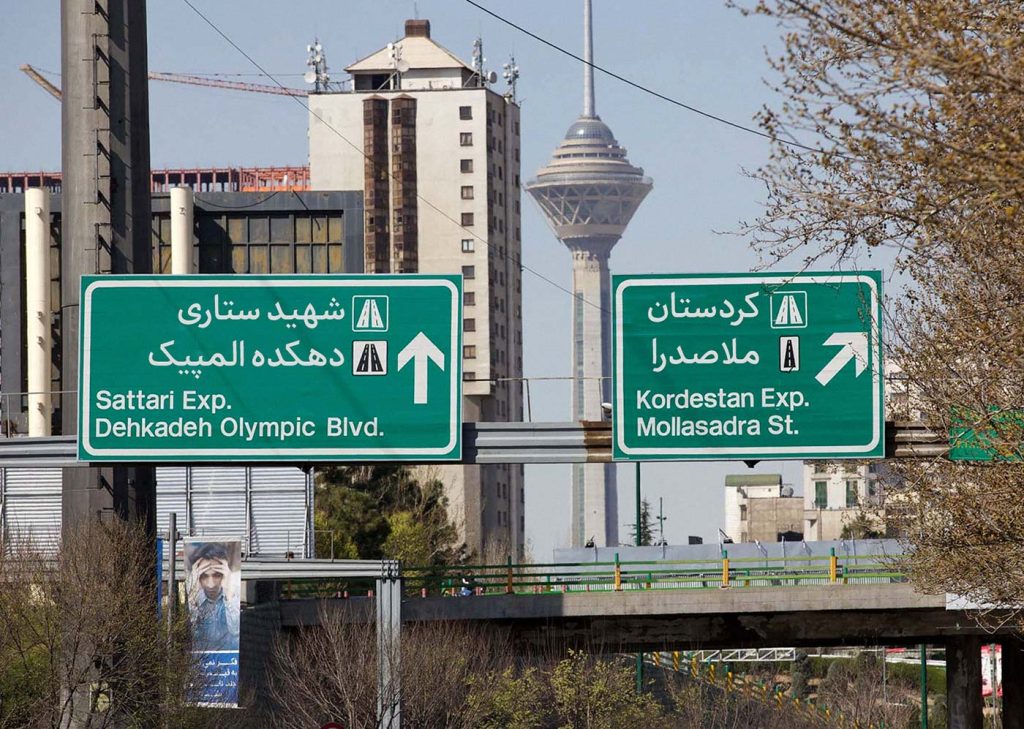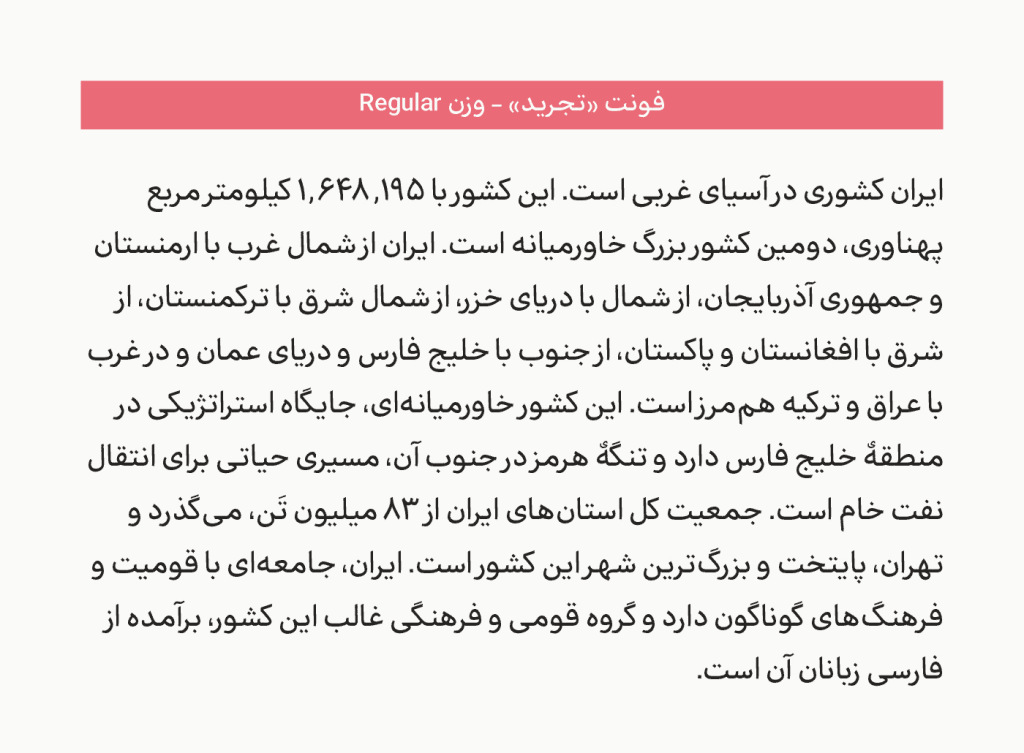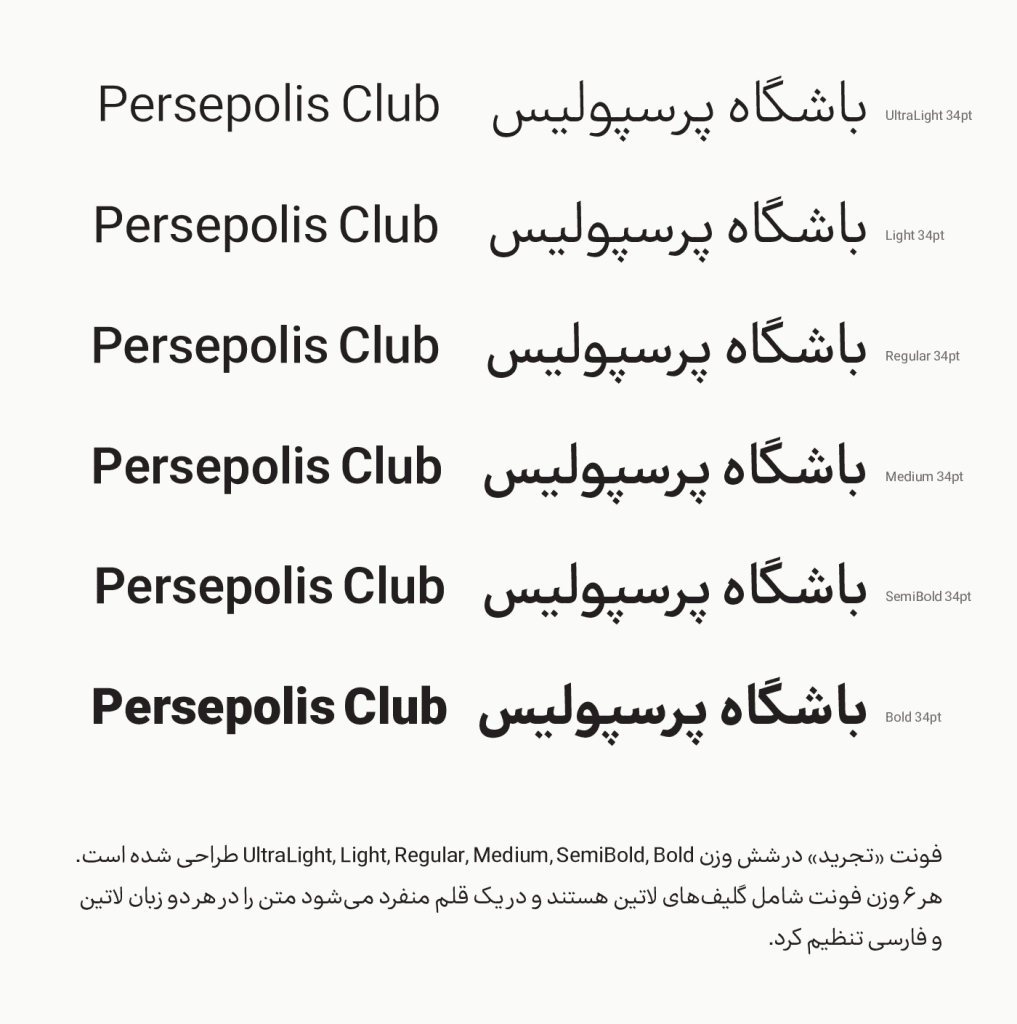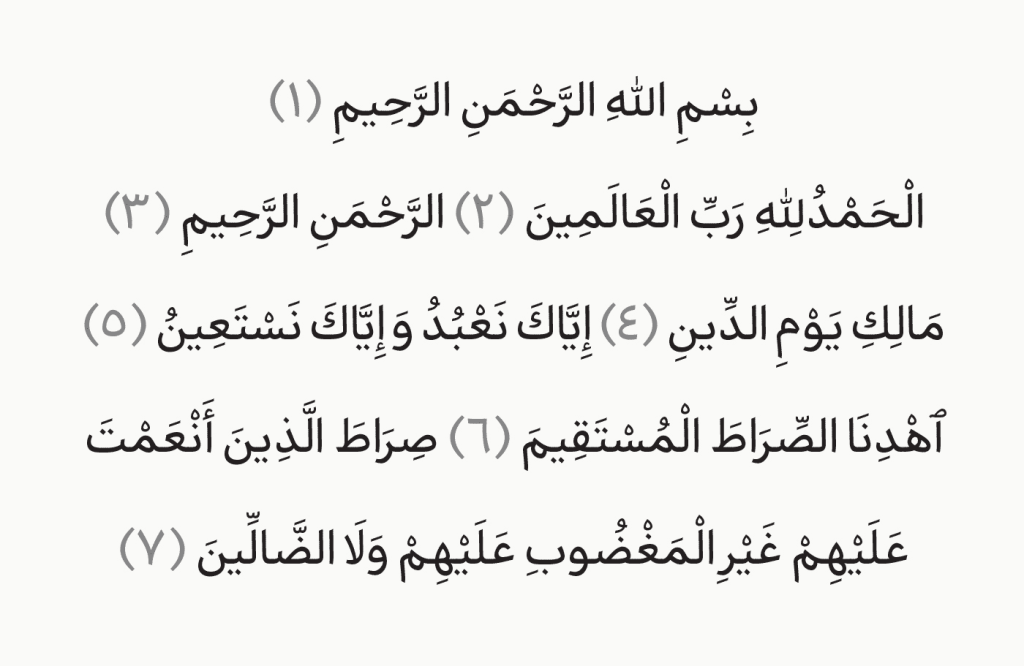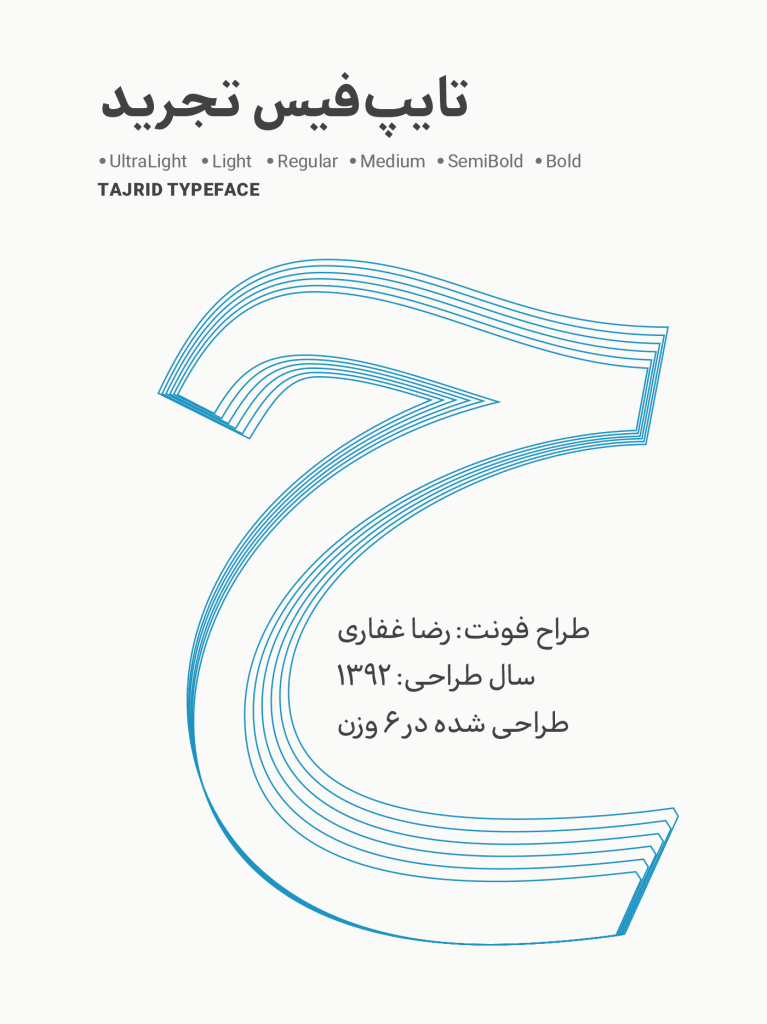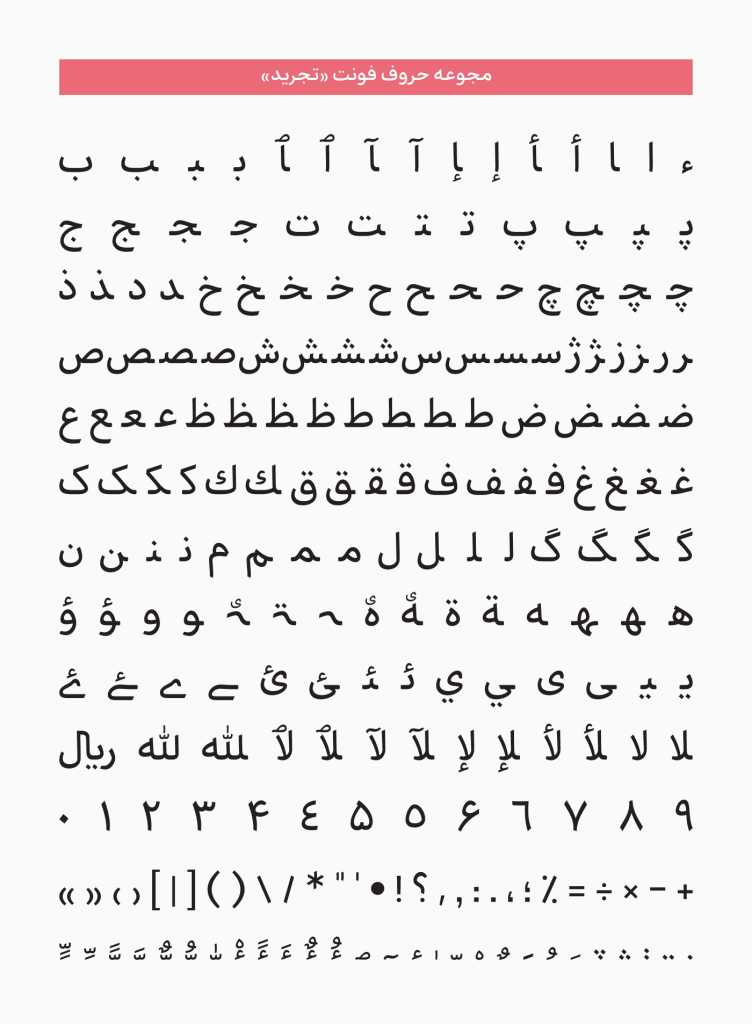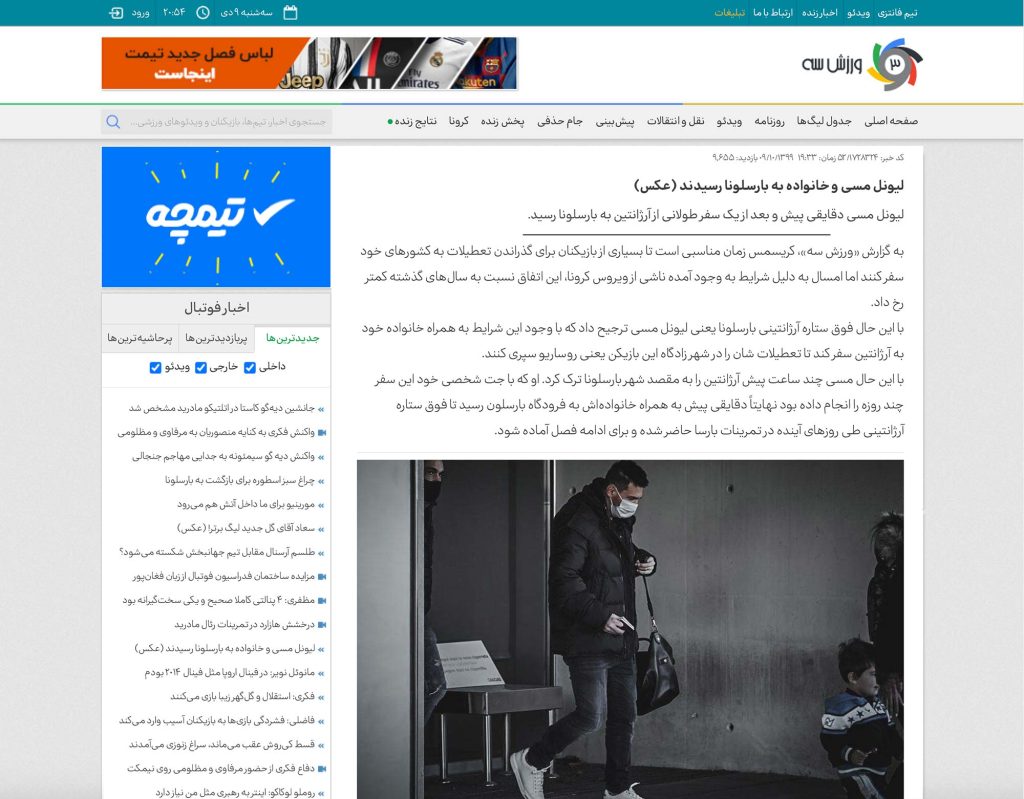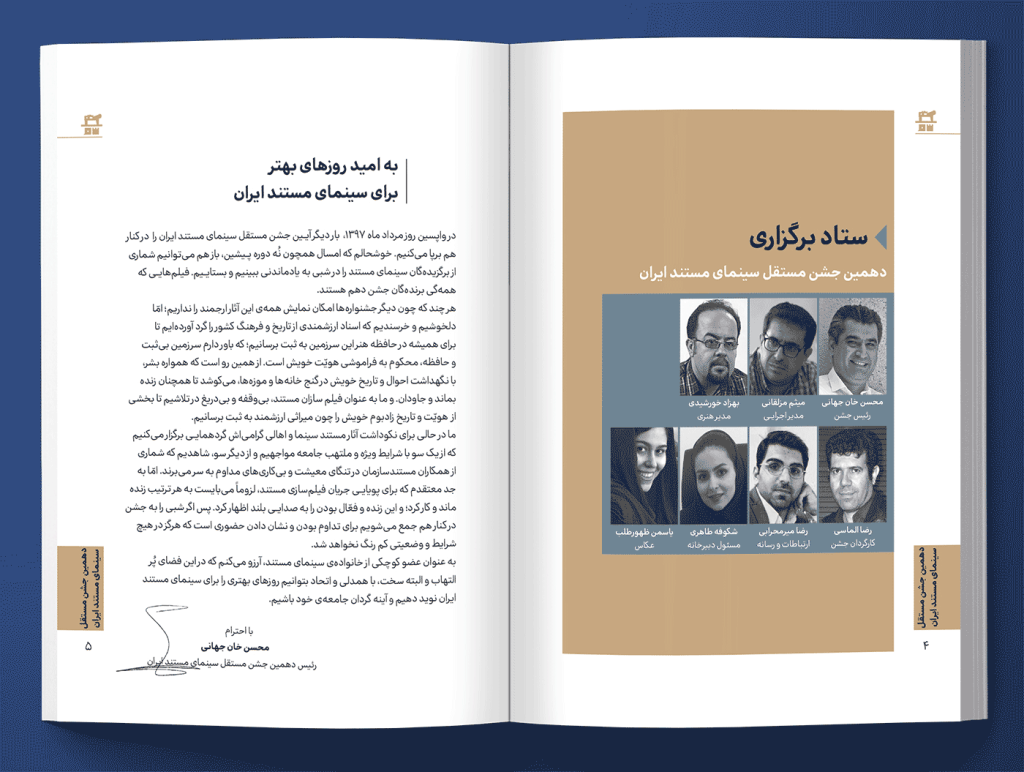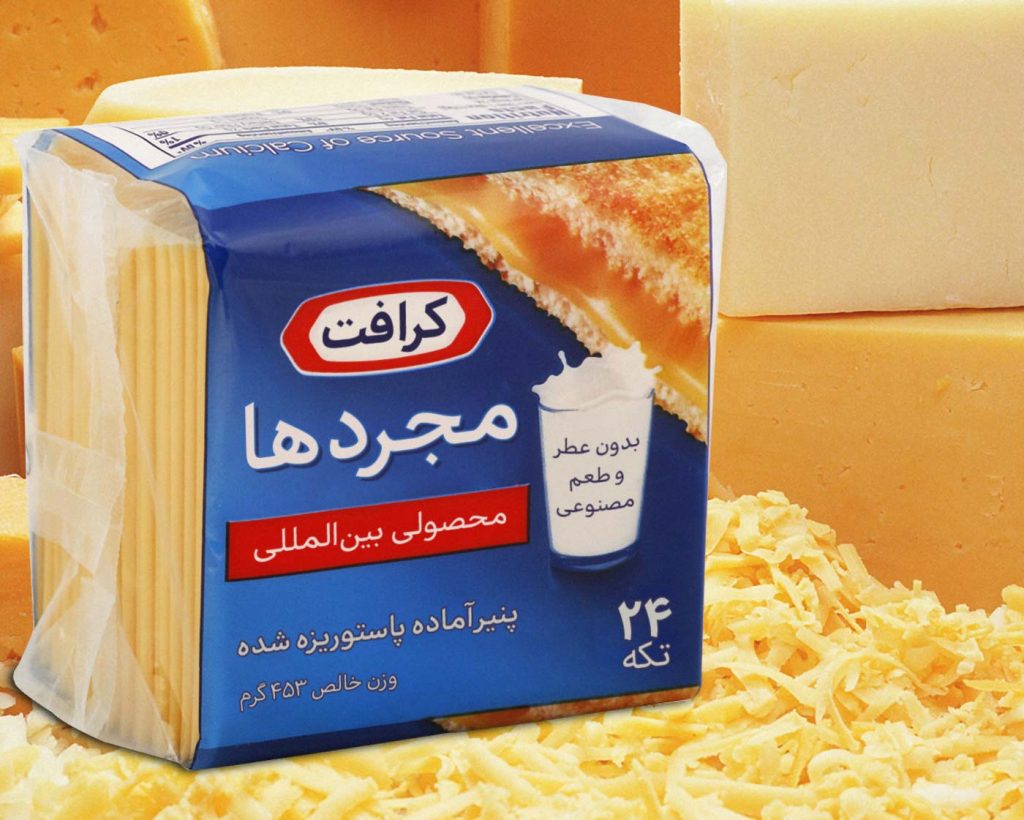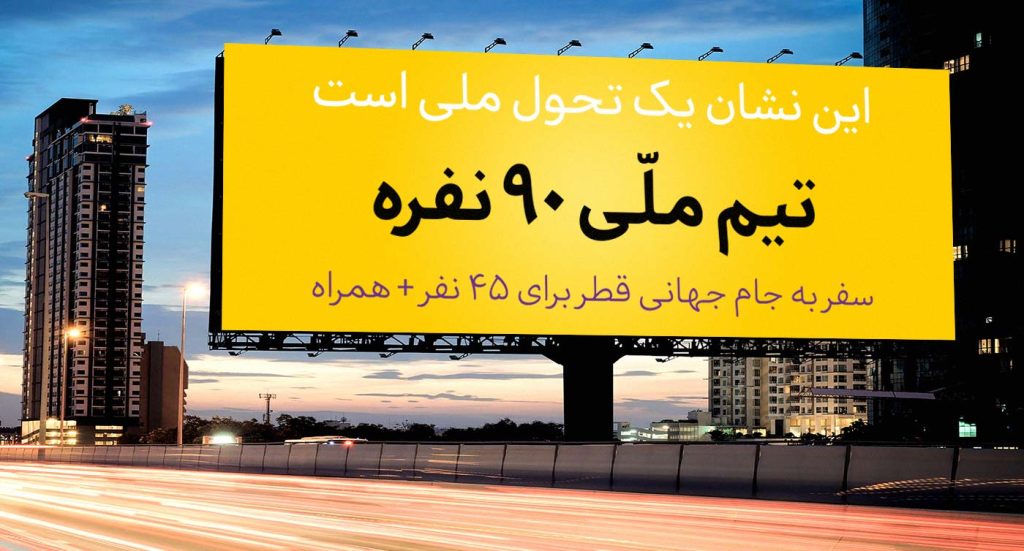
فونت تجرید قلمی خوانا در متون بلند
فونت تجرید قلمی که بر خوانایی این قلم اهمیت و همت فراوان رفته است و همچنین با بهره بردن از جذابیتهای بصری و فرمی خط نسخ و درنظر گرفتن برتری نسبت سطح به دور، طراح توانسته است این تایپ فیس را به عنوان چهرهای محبوب در صفحات وب و اسکرین معرفی نماید.
همچنین در طراحی این قلم سعی بر آن رفته است تا با تنظیم نسبت ارتفاع و اندازه حروف و کرسیها، محصولی و نتیجه ای منطبق با نیازهای روز و امروزی صفحات وب، اسکرین و طراحی گرافیک در اختیار کاربر و خوانندگان قرار گیرد و الگوی کلی و بافت خاکستری متن آن برای استفاده در پیکربندی صفحات وب، اسکرین و صفحهآرایی و … مناسب باشد.
فناوری اوپن تایپ قلم تجرید
این قلم با تنظیم فاصله ها و کرنینگهای متناسب به متن جلوهای پویا و با نشاط می بخشد. فناوری دیجیتال با اجازه دادن به کاراکترهای گسترده و برخی از نمادهای اضافی، اعرابگذاری دقیق و همچنین با امکان استفاده از جایگزینهای متنی این امکان را به وجود آورده تا طراحی متن را بهبود ببخشد و به این ترتیب نحوه تعامل و شیوه استفاده طراح و تجربه کاربری او در کار با صفحات وب، اسکرین و متن را ارتقا داده است.
خانواده 6 وزنی تجرید
این تایپ فیس خوانا دارای شش وزن مختلف است. که طیف تقریبا کاملی از اوزان متفاوت را برای رفع نیاز های شما مرتفع می سازد. . این قلم ضمن پشتیبانی از زبان لاتین ساختار حروف ها و گلیف ها را طبق استاندارد جهانی یونیکد ساخته در تمامی محیطهای متنی و نرمافزاری که از خط فارسی پشتیبانی میکنند قابل استفاده است.
از نقطه نظر شباهت و هم خانوادگی می توان فونت نورا را بسیار شبیه به این قلم در نظر گرفته که خوانایی بالایی هم در متون بلند دارد . شما عزیزان می توانید در تصاویر نمونه زیر با ویژگی ها و جاذبه های بصری این قلم بیشتر آشنا شوید